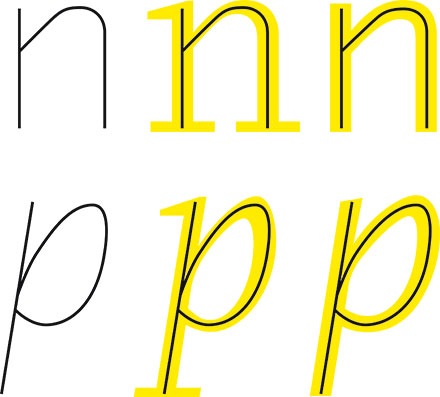
Grotext – der Name ist Programm! ;-)
It is not one of the polished sanserifs. Grotext preserves a human touch. And history. Whereas most contemporary typefaces assimilate lowercase and uppercase, Grotext does the opposite and emphasizes the difference: Its narrow lowercase make it a space-saver. Its uppercase are wide & classically proportioned. This is reminiscent of blackletter combined with uncial forms. Yet its shapes give it a technical flair.
los jetzt bitte. Mich interessiert Eure Fachmeinung zu dieser Schrift und ich bin schon recht gespannt, Eure Kommentare zu lesen.
Mir gefällt sie ungemein gut. Und ich kann - als Nicht-Kreativer - nicht einmal genau sagen, warum. Sie spricht mich einfach an. Weil sie nicht so glatt, ohne Charakter (nicht zu verwechseln mit charakterlos) und eigene Ausstrahlung ist. Das Gemeine-g gefällt mir in dieser Form sowieso und die Bold-Version gefällt mir am besten.
Ich kann damit nichts anfangen. Für meine Sensoren zu "normal" für diese Art von Lebendigkeit. Oder zu lebendig für den Grundton der Schrift. Das beisst sich … Ist jetzt ein Schnellschuss, da man die Schrift bestimmt erst beurteilen kann, wenn man diese ausgedruckt vor sich sieht, hehe.
Die Tiptoe ist viel eher etwas für meine Geschmacksnerven.
auf die schnelle: den style mag ich und sie erinnert mich ein
wenig an die profile - auch wenn die grotext natürlich viel
bewegter ist. nur mit dem kleinen g und den anführunsgzeichen
kann ich mich spontan nicht anfreunden ...
my 2 cent: das Besondere, Einzigartige und noch nie Dagewesene („It is not one of the polished sanserifs. Grotext preserves a human touch. And history …“) kann ich nicht erkennen. Sie ist eine unter vielen schönen Serifenlosen.
... haut mich nicht vom Hocker ... irgendwie sieht das so aus, als hätte jemand TheSans-Versalien mit den "begradigten" Gemeinen der Kosmik kombiniert.
ein vergleich mit the sans und kosmik finde ich unfair, so geshen könnte man bei vielen schriften das gleiche tun, ist aber nicht sinn der sache.
ich stehe nicht auf solche schriften und habe mit manchen zeichen ein paar probleme, für die aber die sowas gerne benutzen und brauchen ist es eine gelungene familie, die solide ausgebaut ist.
ein vergleich mit the sans und kosmik finde ich unfair
... sorry, aber ich will die Schrift nicht runtermachen, die wird sicher ihre Liebhaber finden. Nur war das wirklich das Erste, was mir in den Sinn kam. Liegt vielleicht auch an der Verwendung auf dem Beispielbild, denn die Kosmik ist ja eine Lieblingsschrift für Kinderbuchumschlaggestalter ...
also das a finde ich toll. die leichteren schnitte gefallen mir dabei besser
als die stärkeren. und ich finde fast das die großbuchstaben weniger
charakter haben als die kleinbuchstaben.
was mir nicht gefällt sind m und n. sieht aus als würden die hinken und das
letzte bein nachziehen.
ansonsten sehe ich es wie bertel:
»Sie ist eine unter vielen schönen Serifenlosen.«
Doch, ich finde sie auch klasse und sehe das Besondere in der Schrift, mir gefällt sie gut. :)
Was ich allerdings wirklich ganz fürchterlich finde sind die Anführungszeichen: Diese einfachen Keile sind aggressiv und hässlich (viel zu schräg und unrund) und missverständlich (mit Zollzeichen zu verwechseln) und stören beim Lesen ungemein, während die doppelten Guillemets auf mich albern und aufgesetzt wirken mit den verschieden großen ‘Pfeilen’. Da kann ich wirklich nichts Gutes dran finden, Anführungszeichen müssen unaufdringlich aber deutlich sein, diese hier sind gleichzeit undeutlich und aufdringlich.
Ich will auch! Aber ohalätz! Mir gefällt die linke untere Rundung am i-Punkt in einem Schnitt vielleicht ganz und gar nicht. Und dass das A nicht wie das B ausschaut ... oh elendigliches Elend, unsägliches!
Mann-o-Mann!
Bin ich froh, das mir das Detail im Ganzen aufgeht.
Aber echt ...
Als durchgängiges Prinzip (zumindest bei den Kleinbuchstaben) scheint mir der Gestalter die Trichterform für jedes Zeichen gewählt zu haben. Find' ich schön.
Leider findet sich dieses Prinzip bei den Großbuchstaben nicht wieder.
Außerdem: «Aus dem „n“ mach ich mal ganz schnell ein „u“», denkt sich der sparsame Mensch ... ist hier wohl in die Hose gegangen.
Somit bin ich nicht ganz so begeistert.
Und was lehrt mich Nicht-Kreativen dies nun?
Zehn Kreative, 13 unterschiedliche Detail-Meinungen und eine Glosse auf eben diese.
Also doch alles letztendlich "Wem's gefällt..."?
Ihr müßt doch aussagen können, ob der Font rein handwerklich sauber erstellt wurde. Ob Ihr der Meinung seid, der Font findet seine Nische im Markt neben den genannten Schriften. Wie seht Ihr das Preis-/Leistungsverhältnis? Gibt es Merkmale bei dieser Schrift, die Ihr auf keinen Fall für Eure Gestaltungen akzeptieren könntet?
Ich muß unbedingt schriftmuster machen, die die versteckten besonderheiten von Grotext zeigen, zum beispiel:
– Automatische versalsperrung im versalsatz. Soweit ich sehe, der erste font (Lateinisches schriftsystem), der das bietet und dafür kontextuelle positionierung benutzt. Bei Litteratra war es noch ein alternativer satz versalien.
– Spationierung von satzzeichen über ein 'Formatsatz' feature, also optional.
– Brüche, deren stand sich gemeinen und versalziffern anpaßt.